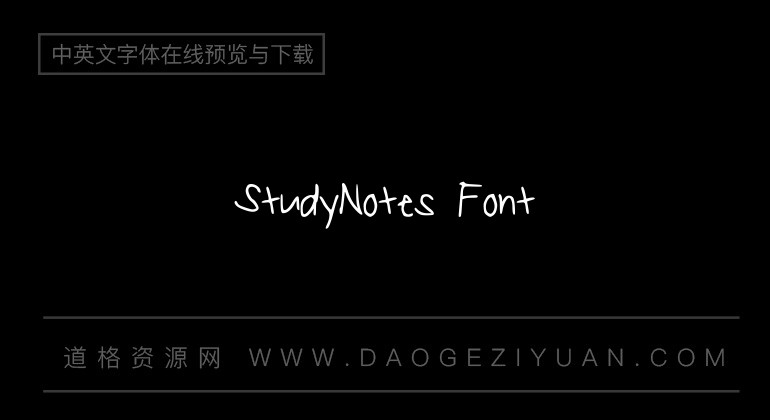
StudyNotes Font 是一种免费的手写风格字体,常用于学术笔记、手册、博客等场合。该字体风格流畅、朴素,适合用于正文,也适合用于标题,能够为文本增添一份温馨的氛围。 StudyNotes Font 的笔画有些粗糙,但仍然易于阅读。这种字体也没有繁琐的装饰和花哨的设计,因此非常适合用于制作教育相关的文档或手写风格的设计中。此外,该字体支持多种语言,包括英语、西班牙语、法语、德语、意大利语等,使其成为了一个全球化的字体选择。内容介绍
StudyNotes Font是一款非常不错的手写艺术字体,具有很好的视觉感,适合于文化类的宣传设计、商业类品牌的广告和产品包装设计以及个性化文字排版等较多场景。